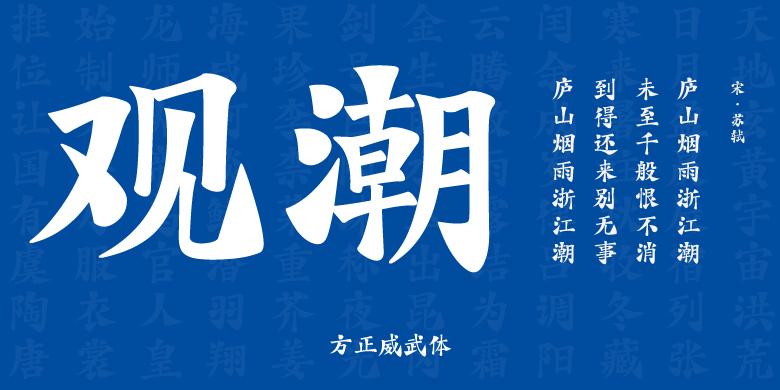
方正威武体
方正威武体,这款字体结构工整、笔画清晰,兼顾美观与易读性,适用于标题、正文、海报、包装、LOGO 等多种场景。字形优雅稳定,风格百搭耐看,适配日常排版与创意设计,让文字呈现更舒适、更具质感。方正威武体一笔一画,皆是细节,以均衡的比例、流畅的线条打造舒适视觉体验,字形端正大气,风格简约现代。无论是商业设计、品牌宣传还是日常排版,都能轻松驾驭,让文字更有格调与力量。方正威武体字体下载。
这是一款手写风格的标题字体,笔画内收外放,遒劲有力,点画如磐石,勾提如刀锋,极具张力和力量感,强化了点、勾、短撇,以及转折处的笔画,笔画粗细对比强烈,使得笔画富有节奏感,从而形成强烈的视觉冲击力。适用于各类需要体现动感的潮流商业品牌推广,以及影视和综艺节目、游戏动漫以及中式餐饮行业。